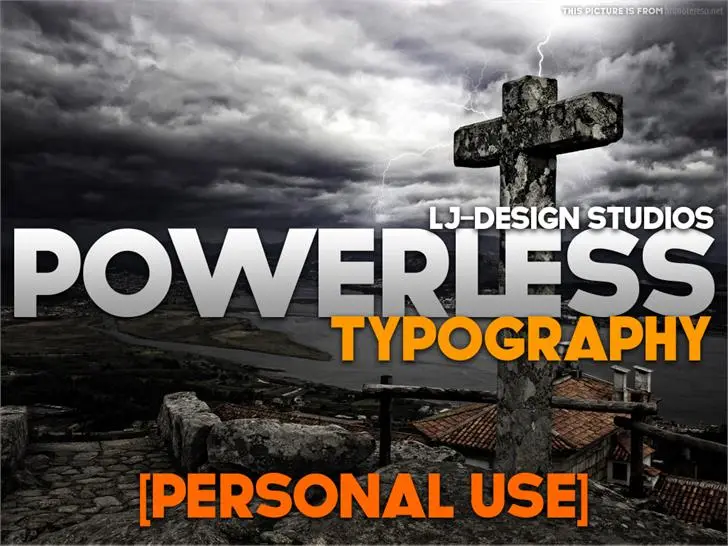
A POWERLESS é uma sans serif que se destaca pela sua simplicidade e modernidade. Originada do trabalho do designer Hamilton, a fonte oferece um estilo clean e limpo que é perfeito para aplicativos digitais e materiais de design gráfico contemporâneos. Ideal para projetos que exigem um forte impacto visual sem se tornarem excessivamente elaborados, a POWERLESS encontra seu melhor uso em logotipos, menus de jogos e interfaces gráficas. Seu desenho limpo permite uma fácil leitura e combina perfeitamente com outras fontes modernas para criar designs atraentes e frescos. Com sua design intuitivo e tecnológico, a POWERLESS pode ser usada em variados projetos digitais como websites, aplicativos móveis, logotipos e materiais de marketing. A fonte é uma excelente escolha para quem busca um estilo elegante e moderno que transmite confiança e poder. Para mais informações sobre acesso comercial e contato direto com o designer Hamilton, visite a página referenciada no site ou entre em contato por email. Não perca essa oportunidade de explorar as possibilidades da POWERLESS.